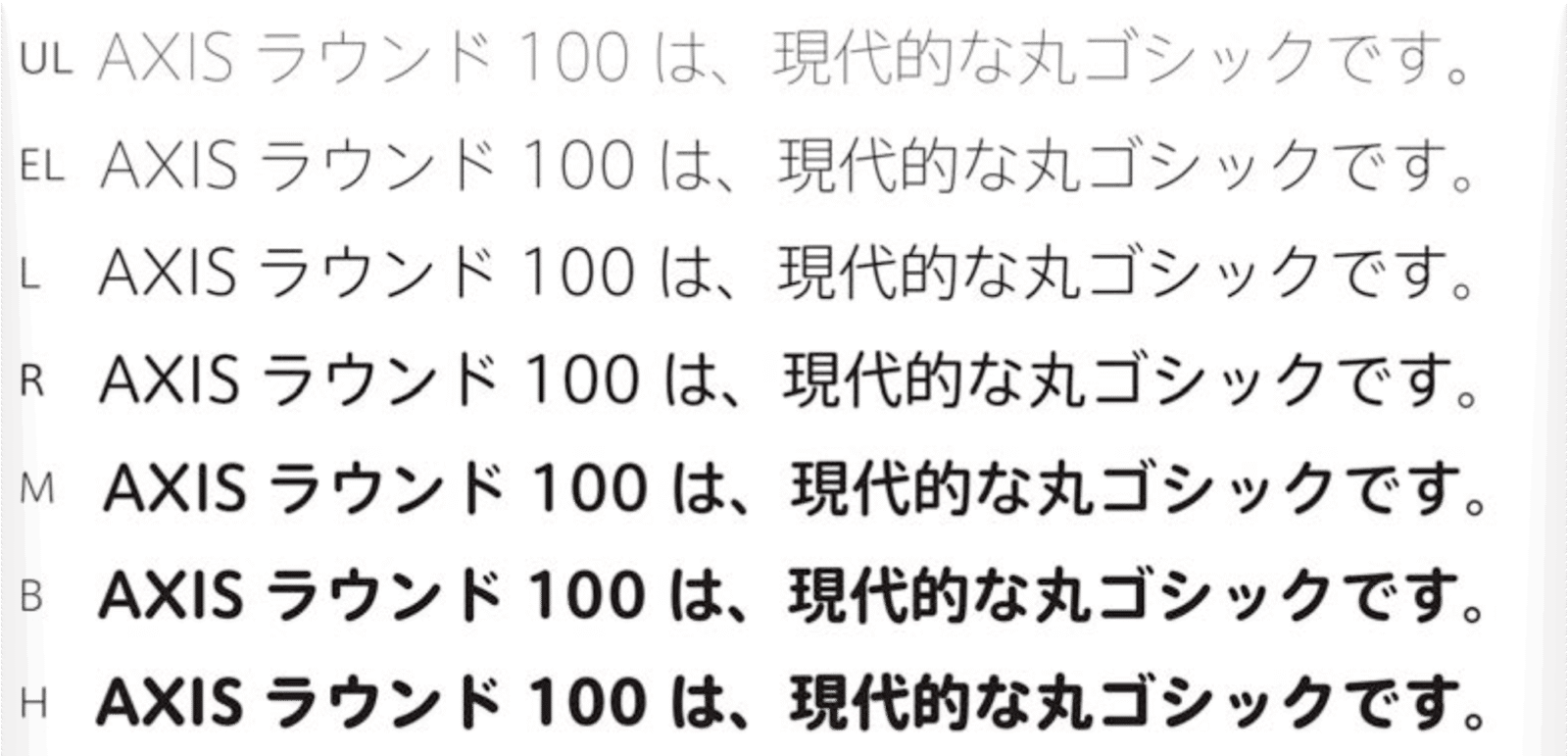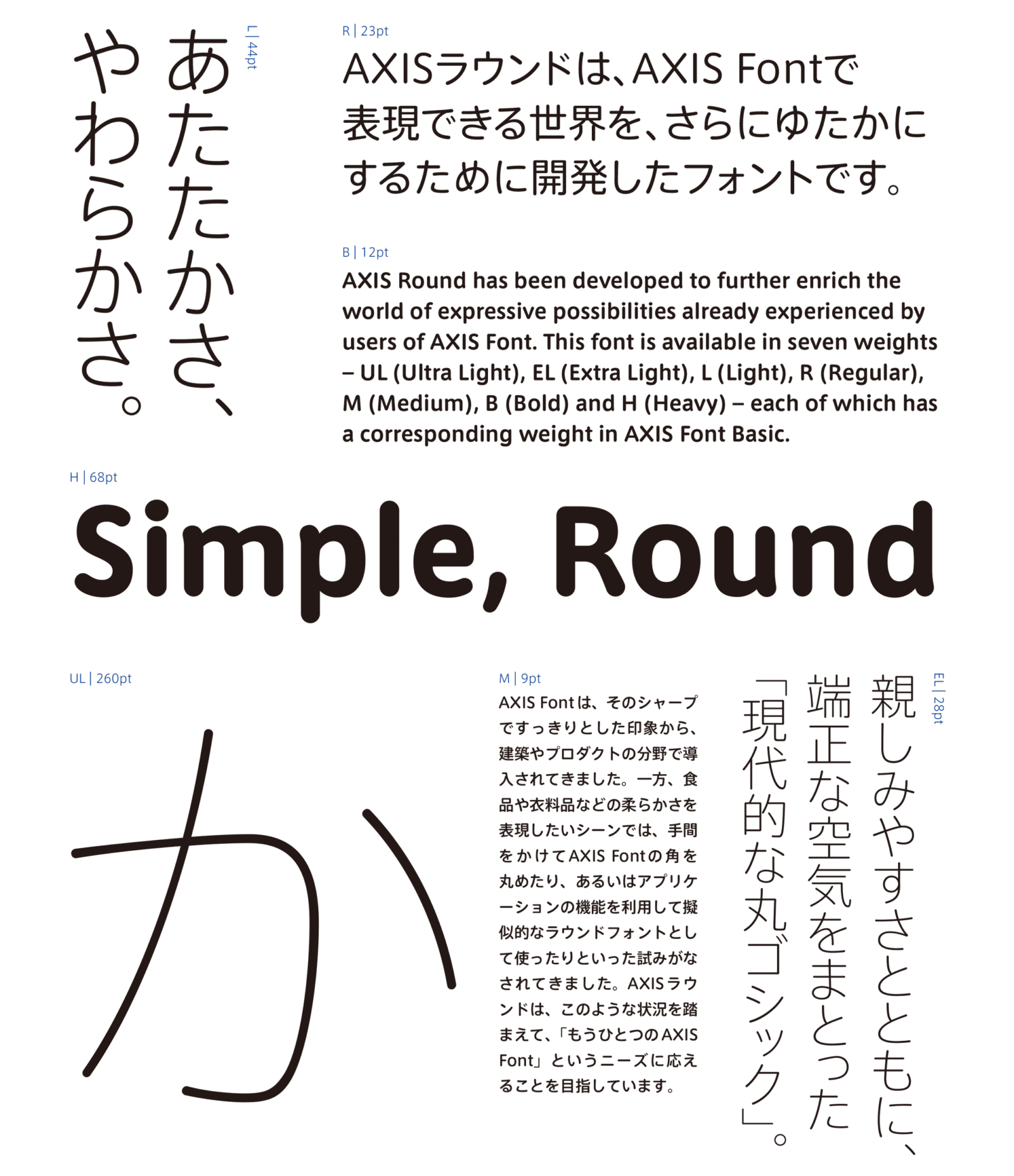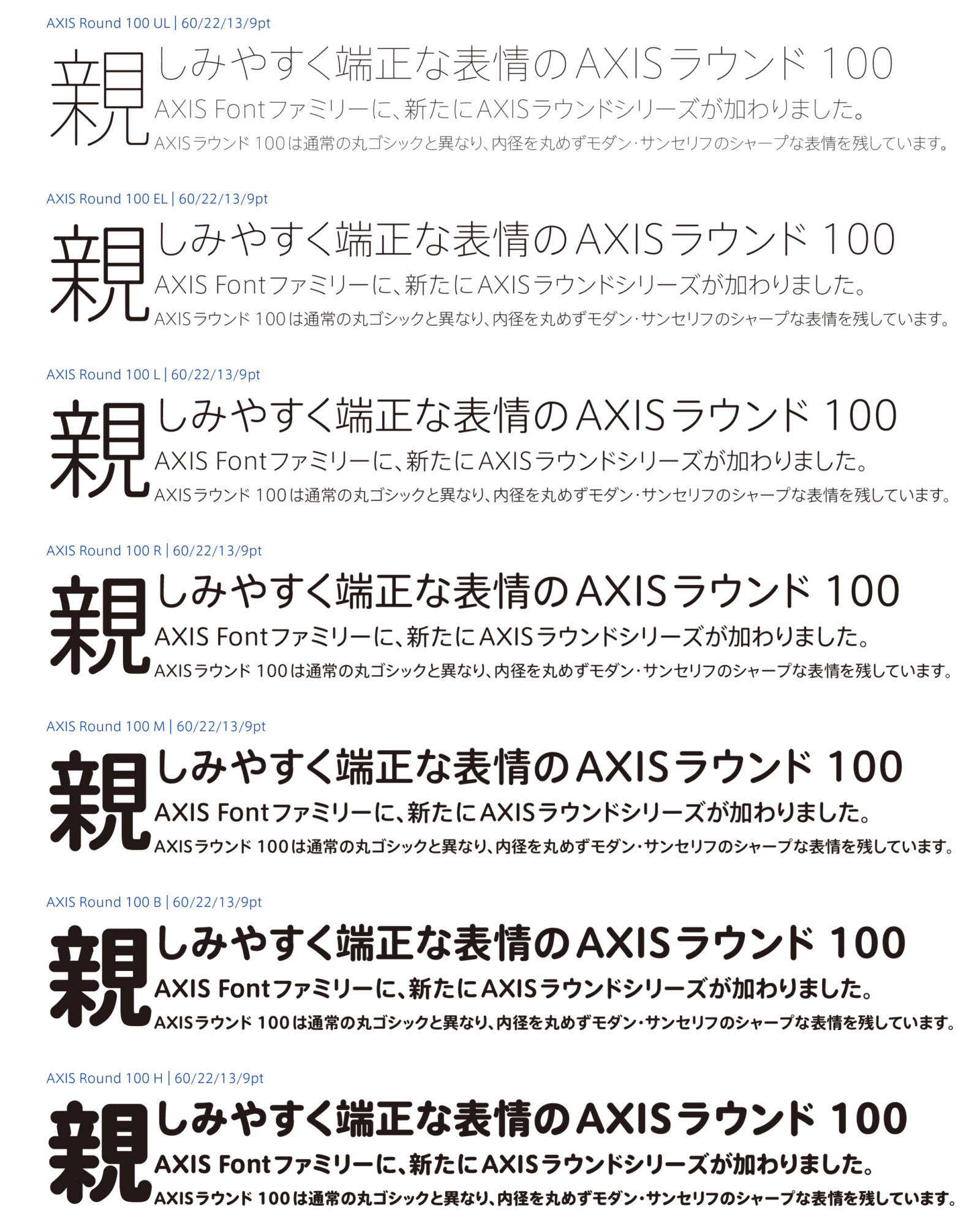
AXIS Font の基本設計を活かした、現代的な丸ゴシック
タイププロジェクト株式会社 (東京都練馬区 代表取締役社長 鈴木 功、以下 タイププロジェクト) は、親しみやすさとともに、端正な空気をまとった新書体「AXISラウンド 100」を発表しました。AXISラウンド 100のデザインは、通常の丸ゴシックとは異なり、内径を丸めていないことによりモダン・サンセリフのシャープな表情を残しています。AXISラウンド 100は、本日より発売を開始いたします。
AXISラウンド 100は、ストロークの先端を直径とする正円を基本とし、丸くすると小さく見える文字はストロークを伸ばしたり、よりなめらかな形になるよう漢字の凹凸を減らすなどの細かな調整をしています。ウエイトは、AXISラウンド 50と同じ、UL (ウルトラライト)、EL (エクストラライト)、L (ライト)、R (レギュラー)、M (ミディアム)、B (ボールド)、H (ヘビー)の 7種類です。
わずかな丸みで穏やかな表情の AXISラウンド 50に対し、AXISラウンド 100は、ストロークの先端がほぼ半円になっています。シンプルでヒューマンな AXIS Font ファミリーに、ふたつのラウンドシリーズが加わることで、さらにゆたかな表情を使い分けることが可能になりました。
タイププロジェクトの代表取締役 鈴木 功は、「AXISラウンド 100は、AXIS Font の基本設計を受け継いだことで、欧文とのマッチングや横組み安定感の高さでポジティブな効果を生み出します。ラウンド系の他の欧文フォントとの相性も良いでしょう。ラウンドシリーズの追加によって、さらに幅広い使用シーンで場面に適した AXIS Font ファミリーをお選びいただくことができるようになりました」と述べています。
AXISラウンド 100